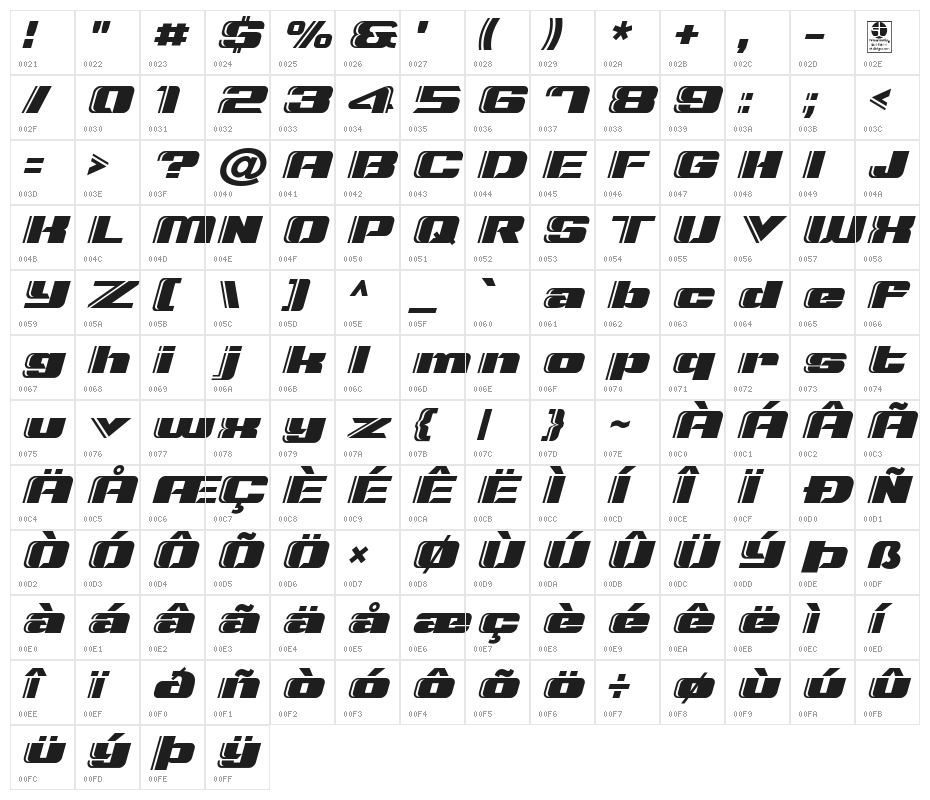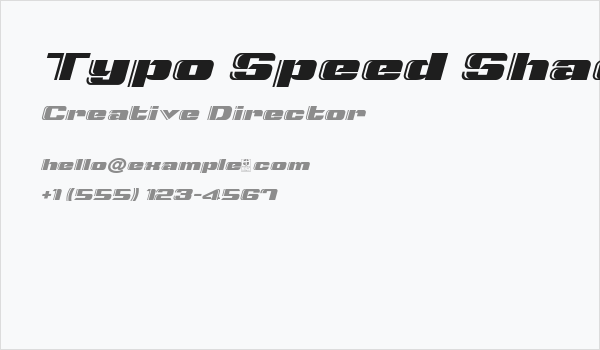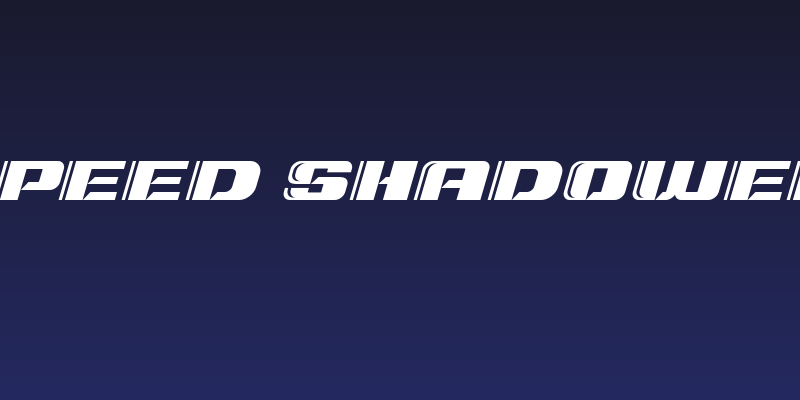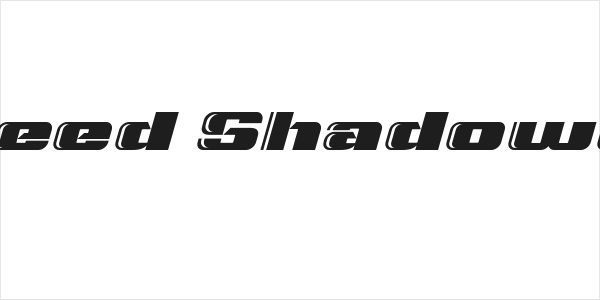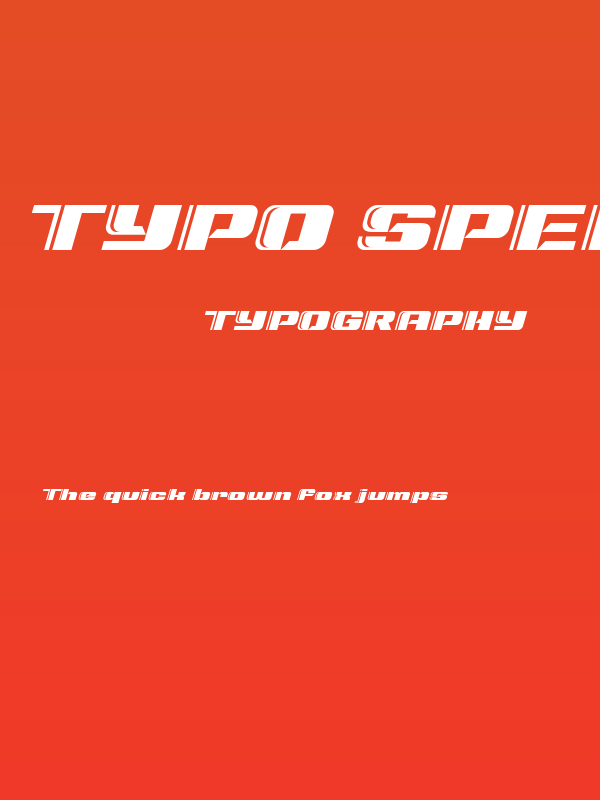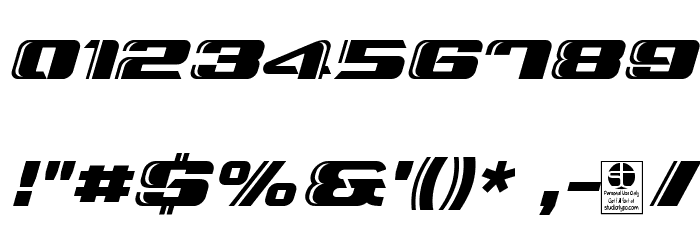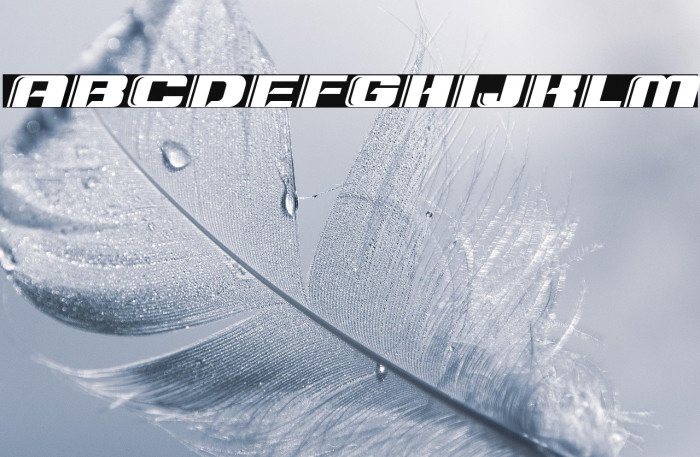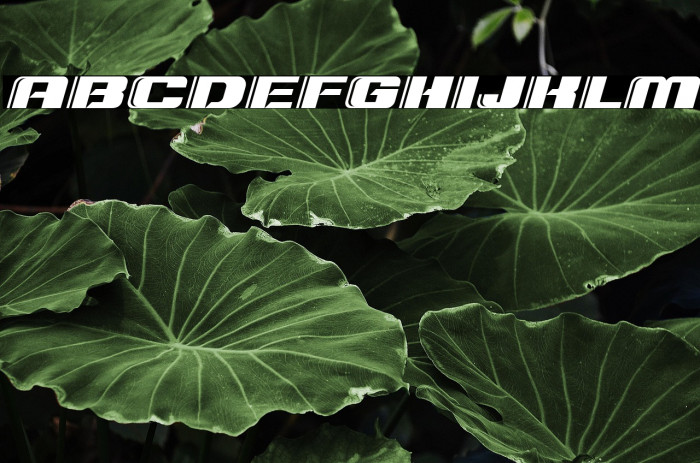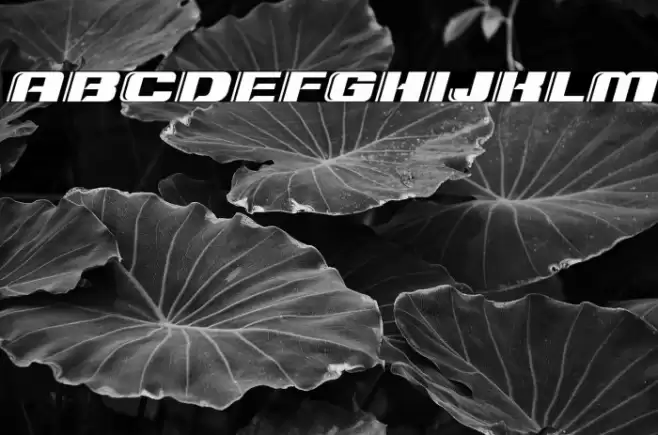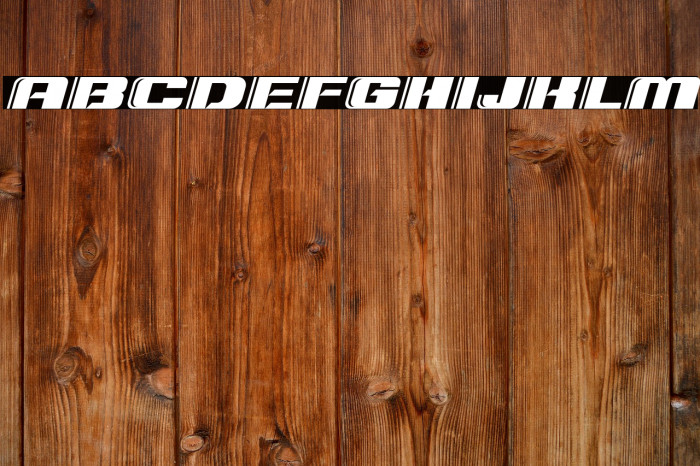
Typo Speed Shadowed Demo Font
| おすすめプロジェクト | Ideal for sports branding, automotive advertisements, dynamic posters, and any project requiring a sense of motion and energy. |